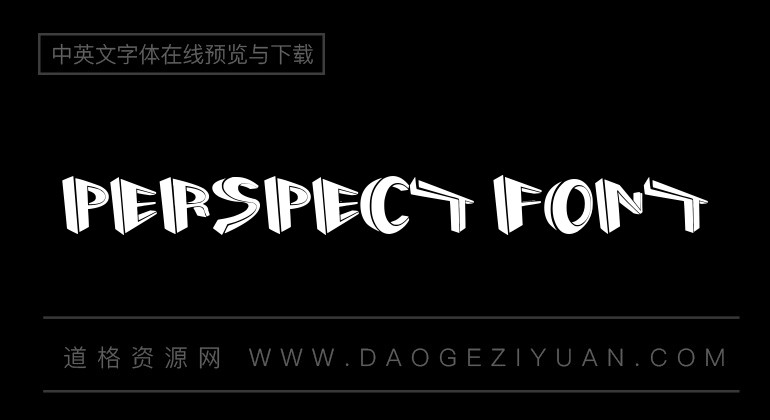
Perspect Font 是一种非常有趣且颇具艺术感的字体,它的设计灵感来源于透视图和立体感。这种字体的每个字母都被设计成具有立体感和深度,这使得它们看起来好像浮在画布上一样。Perspect Font 的设计非常独特,它在设计中采用了许多视觉效果和技巧,使得每个字母都显得非常有趣和引人注目。 Perspect Font 的设计非常适合用于标题、标志、海报和其他需要强烈视觉效果的设计项目。它的字母形状非常清晰和易于辨认,而且在各种尺寸和颜色下都能保持清晰度。如果你正在寻找一种非常独特和引人注目的字体,那么 Perspect Font 可能是一个不错的选择。内容介绍
Perspect Font是一款非常不错的手写艺术字体,具有很好的视觉感,适合于文化类的宣传设计、商业类品牌的广告和产品包装设计以及个性化文字排版等较多场景。